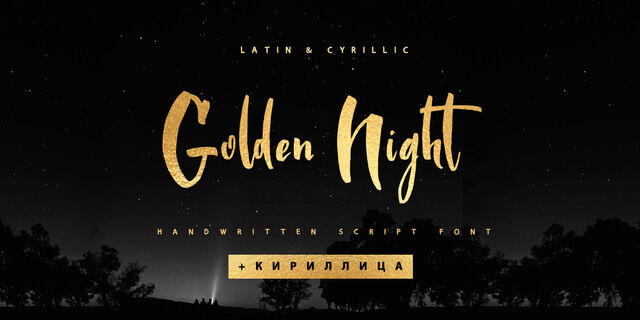
Рукописный шрифт с поддержкой кириллицы, который идеально подходит для брендинга, логотипов, социальных сетей, этикеток, дизайна упаковки и заголовков блогов. Шрифт Golden Night содержит полный набор заглавных и строчных букв, 32 лигатуры в латинице а также 18 лигатур в кириллице которые включены автоматически для создания более естественного рукописного вида. Включена обширная языковая поддержка 31 языка, включая кириллицу для русского, белорусского, украинского и болгарского. Шрифт разработала Ирина Двилюк в 2021 году.
быстрый, артистичный, органический, динамичный, свежий, неряшливый, веселый, легкомысленный, эмоциональный, жидкий, лихой, подвижный, непоседливый, мультяшный, яркий, вкусный, смешной, добрый, милый, мягкий, ремесленный, рукотворный, ручной, дружелюбный, доверительный, зеленый, натуральный, природный, игривый, забавный, прикольный, живой, оригинальный, приветливый, характерный, праздничный, сочный, спелый, крафтовый, радостный, озорной, весенний, летний, счастливый, нервный, прыгающий, танцующий, проворный, вернакулярный, свободный, размашистый, модный, смелый, интересный, энергичный, уверенный, темпераментный, самобытный, художественный, мечтательный, выразительный, амбициозный, заметный, броский, творческий, экспрессивный, активный, мотивирующий, романтичный